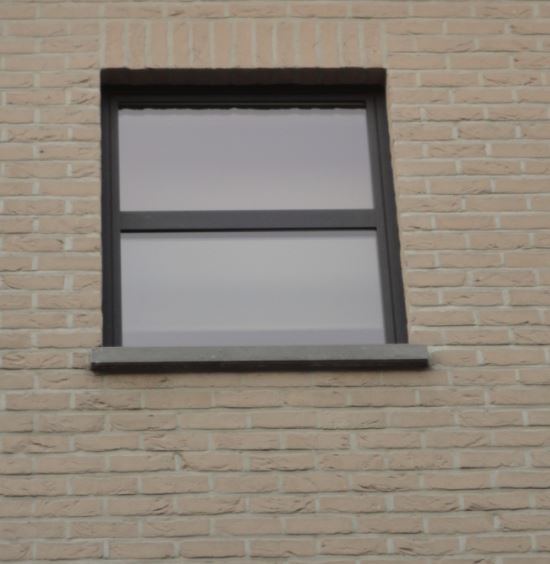
Vandaag laat ik jullie de drie volgende letters zien uit het zomerproject alfabet, namelijk de k, l en de m.
Today I'll show you the next three letters from the summer project alphabet: k, l and m.
Chillida project: P and U
P en U waren de letters voor de uitdaging van deze maand:
| P |
| U |
the (Flint)stones
Ook nog een opdracht van het zomerproject; een opdracht van Mieke: doe alsof je een steenkapper bent. Schrijf je woord uit in een toepasselijk lettertype. Je potlood/pen is je beitel. Je papier is een stenen ondergrond.
Another assignment in the summer project series, one by Mieke: pretend to be a mason/stonecutter. Write your word in an appropriate font. Your pen or pencil is your chisel and your paper is the stone background.
En terwijl ik het woord 'stones' aan het schrijven was, moest ik plots denken aan één van mijn favoriete TV-programma's van vroeger: The Flintstones met natuurlijk Fred en Barney als mijn 2 'helden' van toen:
And while I was writing the word 'stones' , I suddenly had to think about my favourite TV-programme when I was (a lot !) younger: The Flintstones, with 2 of my heroes: Fred and Barney
Another assignment in the summer project series, one by Mieke: pretend to be a mason/stonecutter. Write your word in an appropriate font. Your pen or pencil is your chisel and your paper is the stone background.
En terwijl ik het woord 'stones' aan het schrijven was, moest ik plots denken aan één van mijn favoriete TV-programma's van vroeger: The Flintstones met natuurlijk Fred en Barney als mijn 2 'helden' van toen:
And while I was writing the word 'stones' , I suddenly had to think about my favourite TV-programme when I was (a lot !) younger: The Flintstones, with 2 of my heroes: Fred and Barney
| Fred en Barney |
50 th wedding anniversary
In opdracht van mijn ouders maakte ik deze kaart voor mijn tante en nonkel die eergisteren 50 jaar getrouwd waren en feest vierden. Ik denk niet dat ze van felle kleurtjes houden, dus ik hield het sober.
My aunt and uncle have been married for 50 years, so my parents asked me to make a card for this special occasion.
Eerst met deze stencil en inkt 'gestempeld' op het papier (30 op 15 cm) en gevouwen volgens een model dat ik kreeg van een vriendin (bedankt, M!)
I cut the paper to the size I wanted (30 to 15 cm) and started inking this template on the paper. A friend (thanks, M!) provided me with the folding instructions.
De tekst is geschreven in italic met een speedball pen en zwarte inkt.
Hun initialen: 'L' en de 'W' sneed ik uit met de Cuttlebug en 'Sizzix thinlits brushletters' die ik afgelopen zomer kocht op vakantie in Normandië . De ring-stempel emboste ik in goud.
I used the Cuttlebug and Sizzix thinlits brushletters to cut out their initials: L and W and the ring stamp was embossed in gold. The text was written in Italic with a speedball pen nib and black ink.
'found' letters :A B C
Anns opdracht voor het zomerproject was: verzamel gedurende de hele zomer letters: foto's, afbeeldingen ervan,... en voeg ze samen in een werk.
Nu, het nemen van de foto's was super-leuk en een echte 'eye opener', letterlijk en figuurlijk.
Maar of er nog tijd gaat zijn voor het samenvoegen....dat betwijfel ik. Het nieuwe schooljaar is ondertussen weer van start gegaan en de zomervakantie weer voorbij. Maar wie weet- ooit nog eens....
Het op jacht gaan naar de letters op zich was in elk geval al heel erg plezant en de volgende 7-8 woensdagen, laat ik jullie zien wat ik zoal 'geschoten' heb.🙂
Ann's assignment for the summer project was: collect (pictures of) letters all summer long and bring them together in a piece of art.
Well, the taking of the pictures was a lot of fun to do; a real 'eye opener' in every meaning of the word but I doubt whether I'll still have the time to put the pics together ... The new schoolyear started and the summer holidays are over. But who knows, one day ?
I really enjoyed the 'hunting' for letters and I'll share with you what I 'shot' 😊 on the following 7 or 8 Wednesdays
Today: A, B and C
Vandaag de eerste drie letters:
Nu, het nemen van de foto's was super-leuk en een echte 'eye opener', letterlijk en figuurlijk.
Maar of er nog tijd gaat zijn voor het samenvoegen....dat betwijfel ik. Het nieuwe schooljaar is ondertussen weer van start gegaan en de zomervakantie weer voorbij. Maar wie weet- ooit nog eens....
Dus schilderde ik hem zwart. Zo had ik een mooier contrast met de witte letters én past ie weer op de salontafel....
This is a rock I bought in a shop, the kind you can place a candle in. I didn't like the colour, though, so it ended up in the cupboard. That's why I painted it black. Then you have a nice contrast with the white lettering and now it's on the coffee table again !